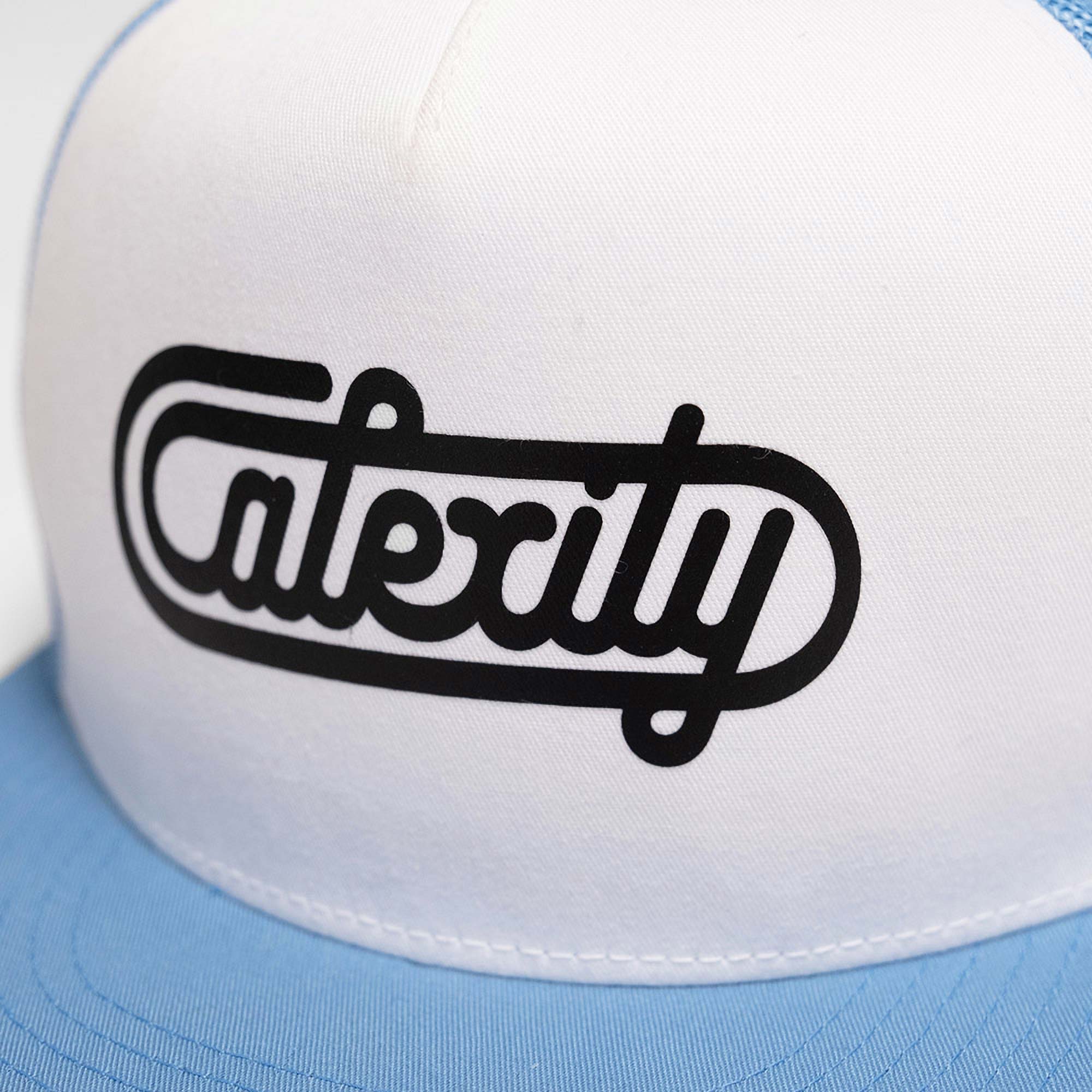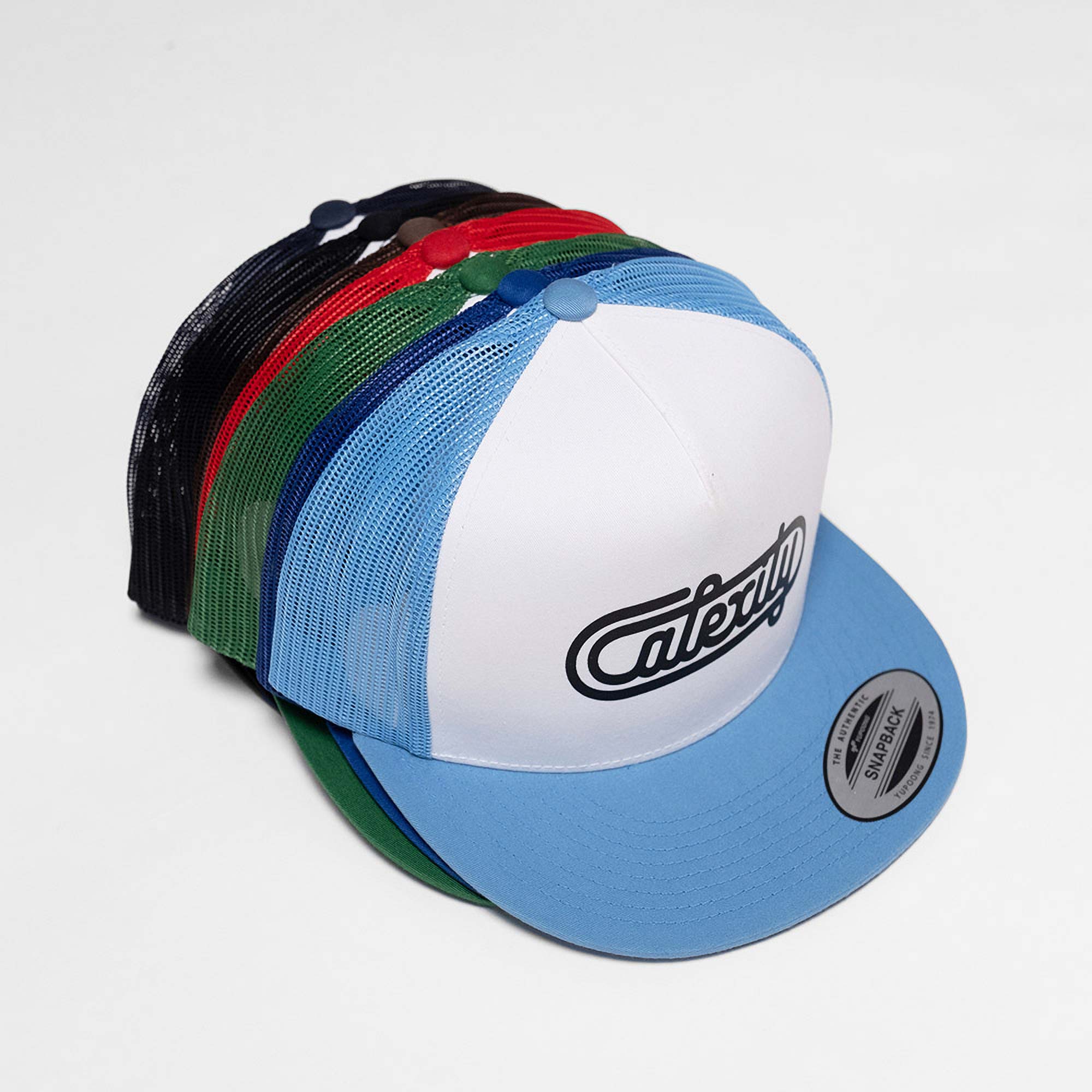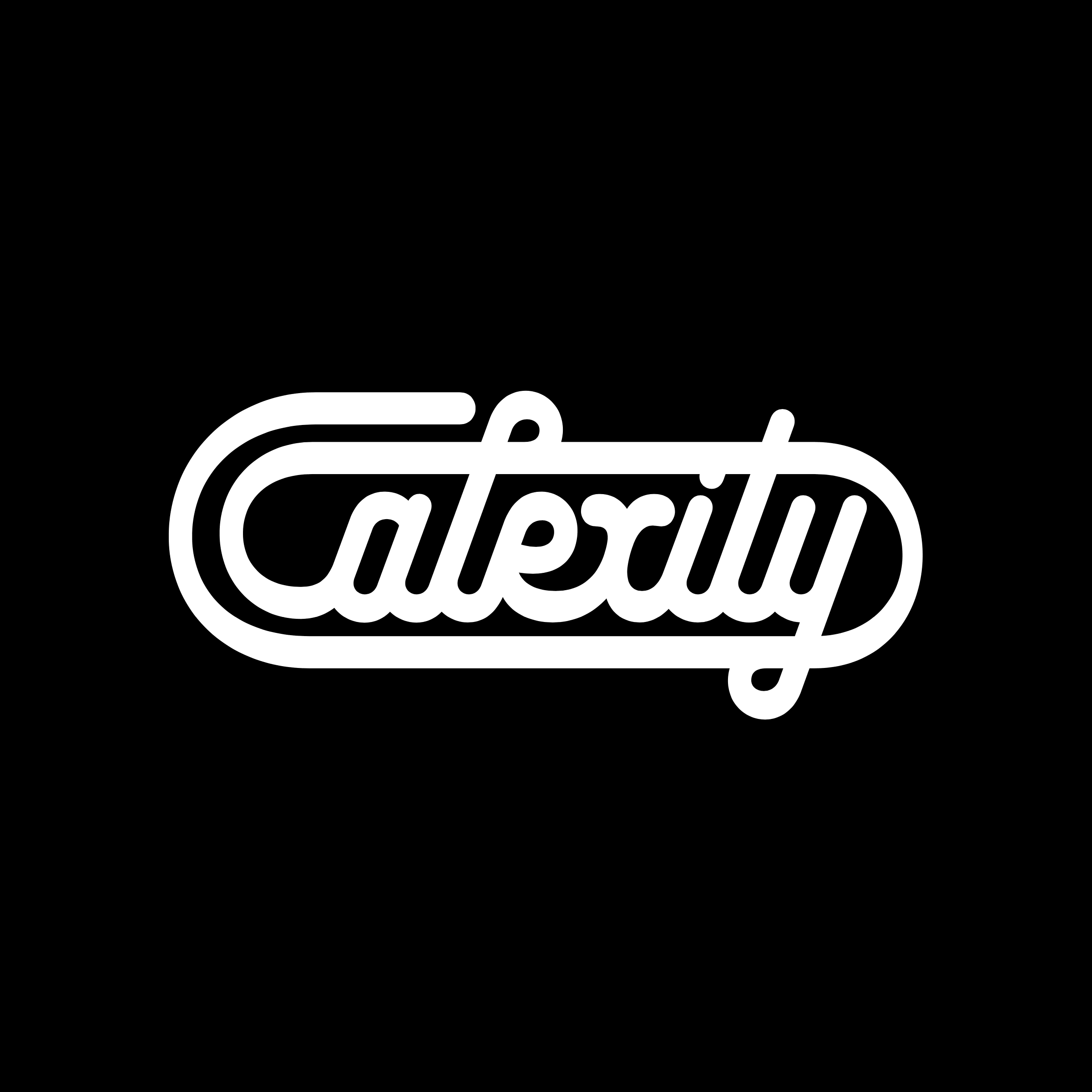
Calexity
Nová interpretácia ikonického loga Calex zo Zlatých Moraviec pre slovenského rapera Veca.
Geometrický kaligrafický lettering je inšpirovaný chladiacou sústavou chladničky, má zaoblené konce ťahov a inverzný kontrast. Písmeno x je konštruované tak, aby ho bolo možné čítať ako ligatúru písmen x a c.